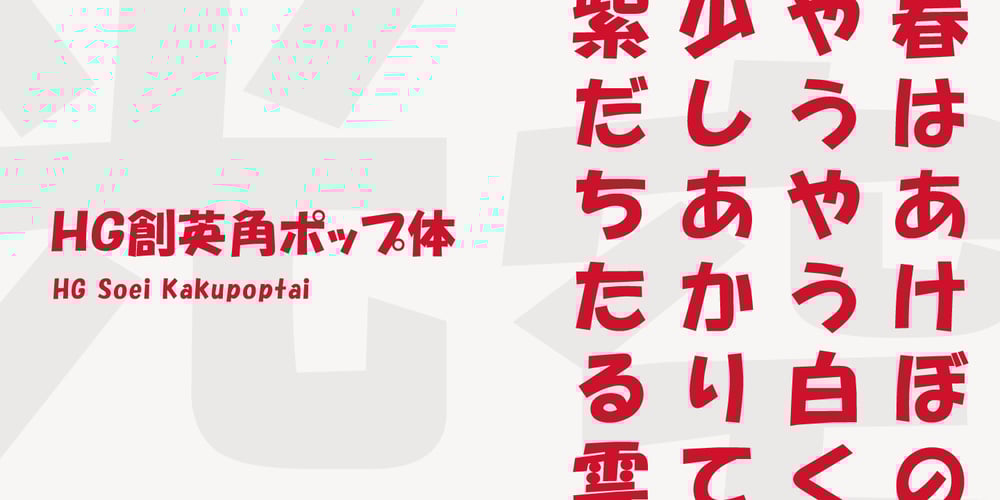
HG Soei Kakupoptai Font Family was designed by published by RICOH. HG Soei Kakupoptai contains 1 styles and family package options. HG創英角ポップ体は、水本恵子氏がデザインした「創英ポップ体1」を字母とする書体です。店頭広告用文字のスタイルを模して作られた書体で、楽しく、軽快な書体です。極太角ゴシックのイメージをベースに作られていますが、それをやや崩し、柔らかさも取り入れ、フリーハンドで書いたイメージを残しています。見やすくするため、ふところは可能な限り大きくなっています。店頭のPOP、チラシ、看板などに最適の書体です。 HG Soei Kakupoptai is a typeface with a “fresh pop” designed by Mr. Mizumoto Keiko. It is a typeface made by mimicing the style of letters for party-style, fun and light typefaces. It is made on the basis of the image of thickSoei Kakugothic, but it breaks it open, and incorporates softness, leaving the font looking freehand. To make it easy to see, the boldness has become as thick as possible. It is a typeface best suited for store-front fun, leaflets, signboards and so on.